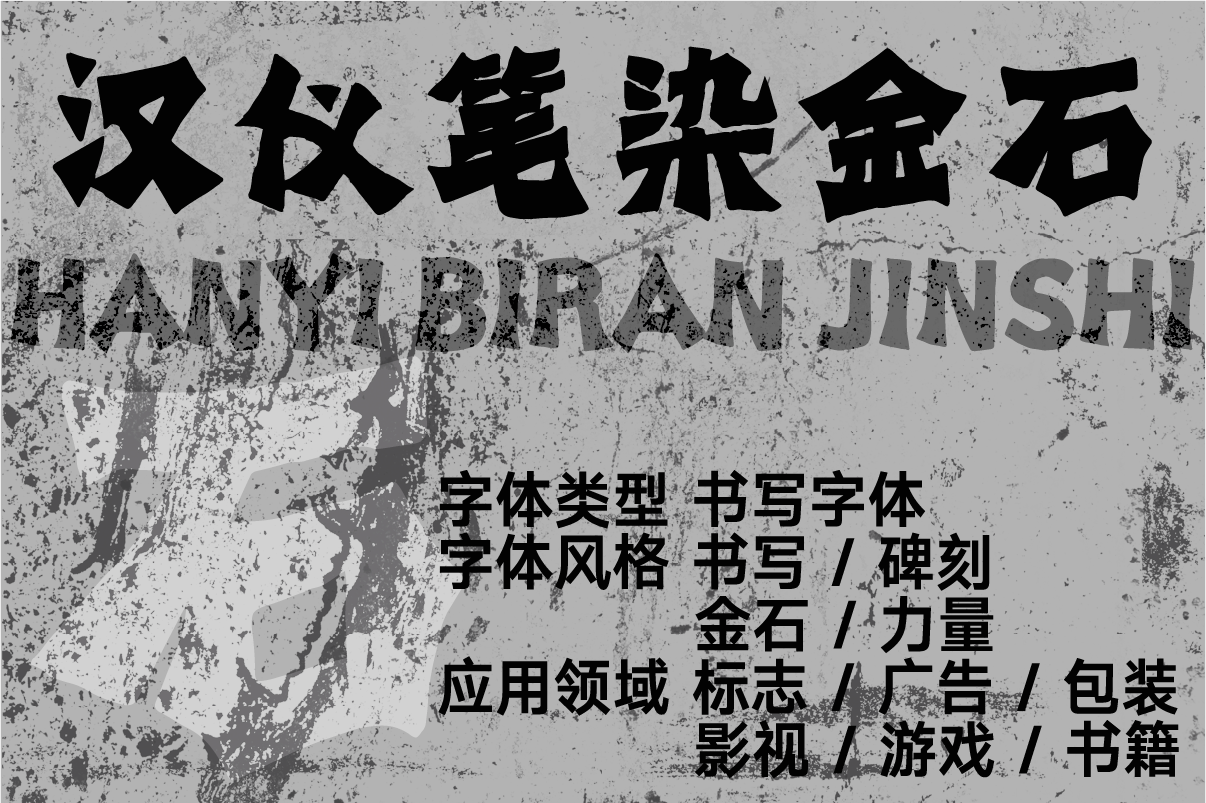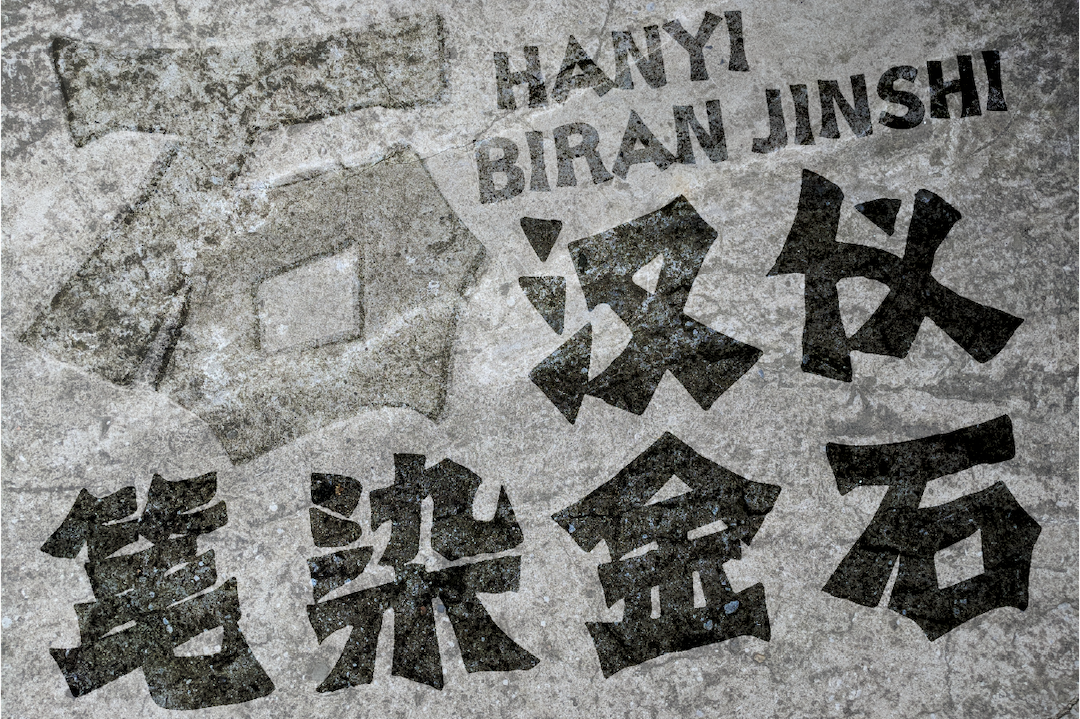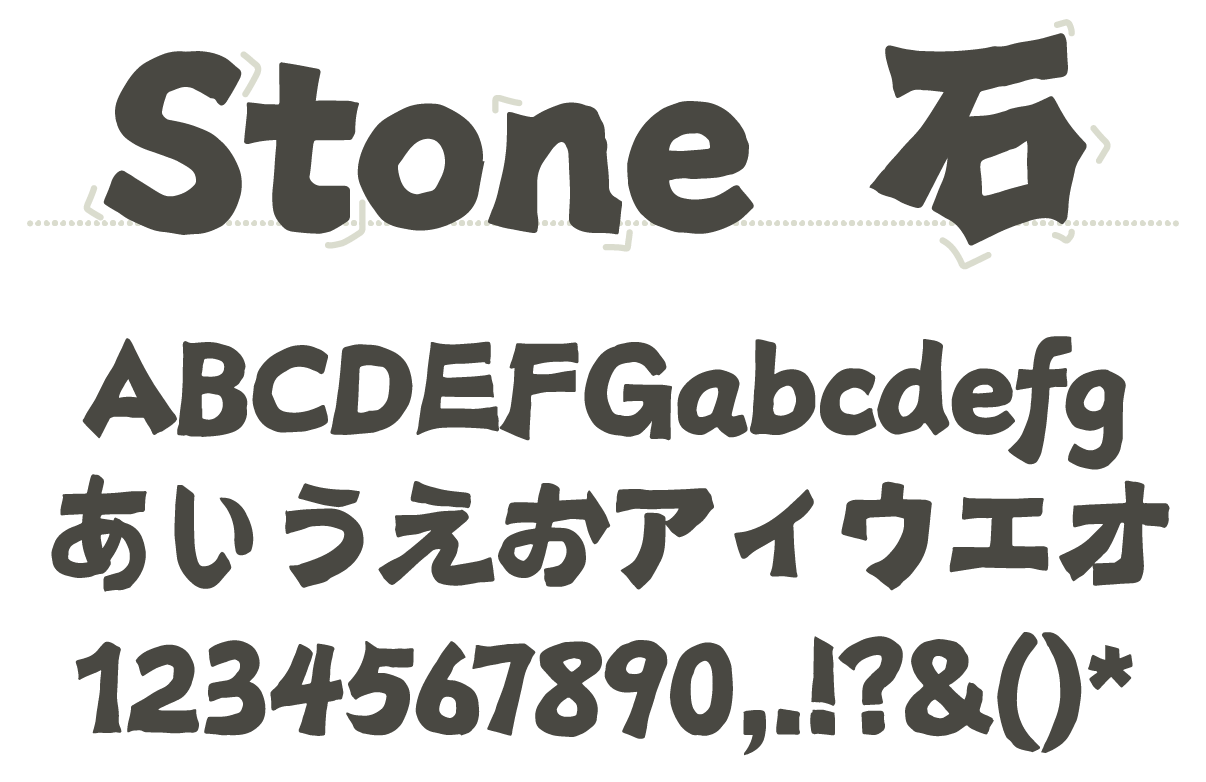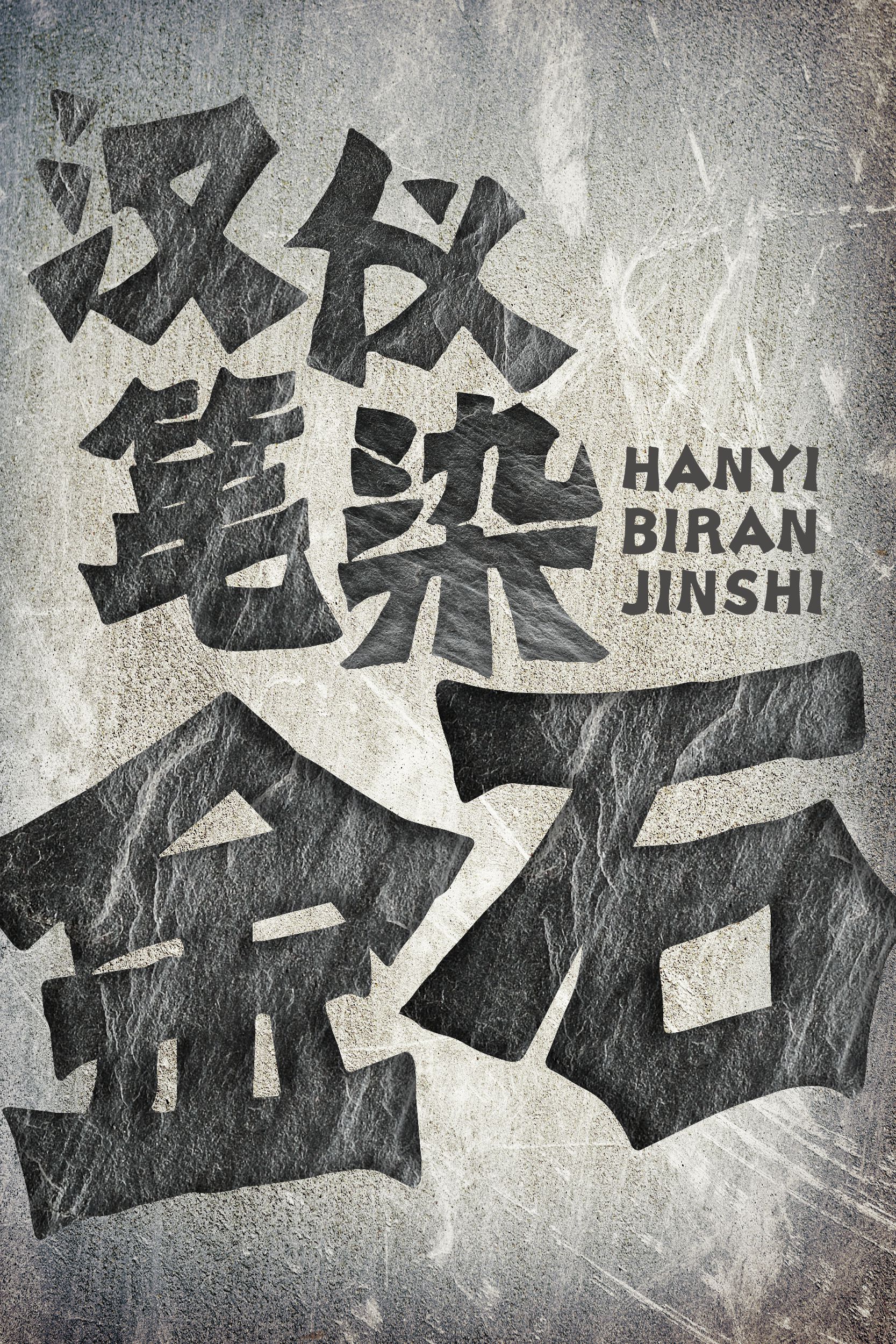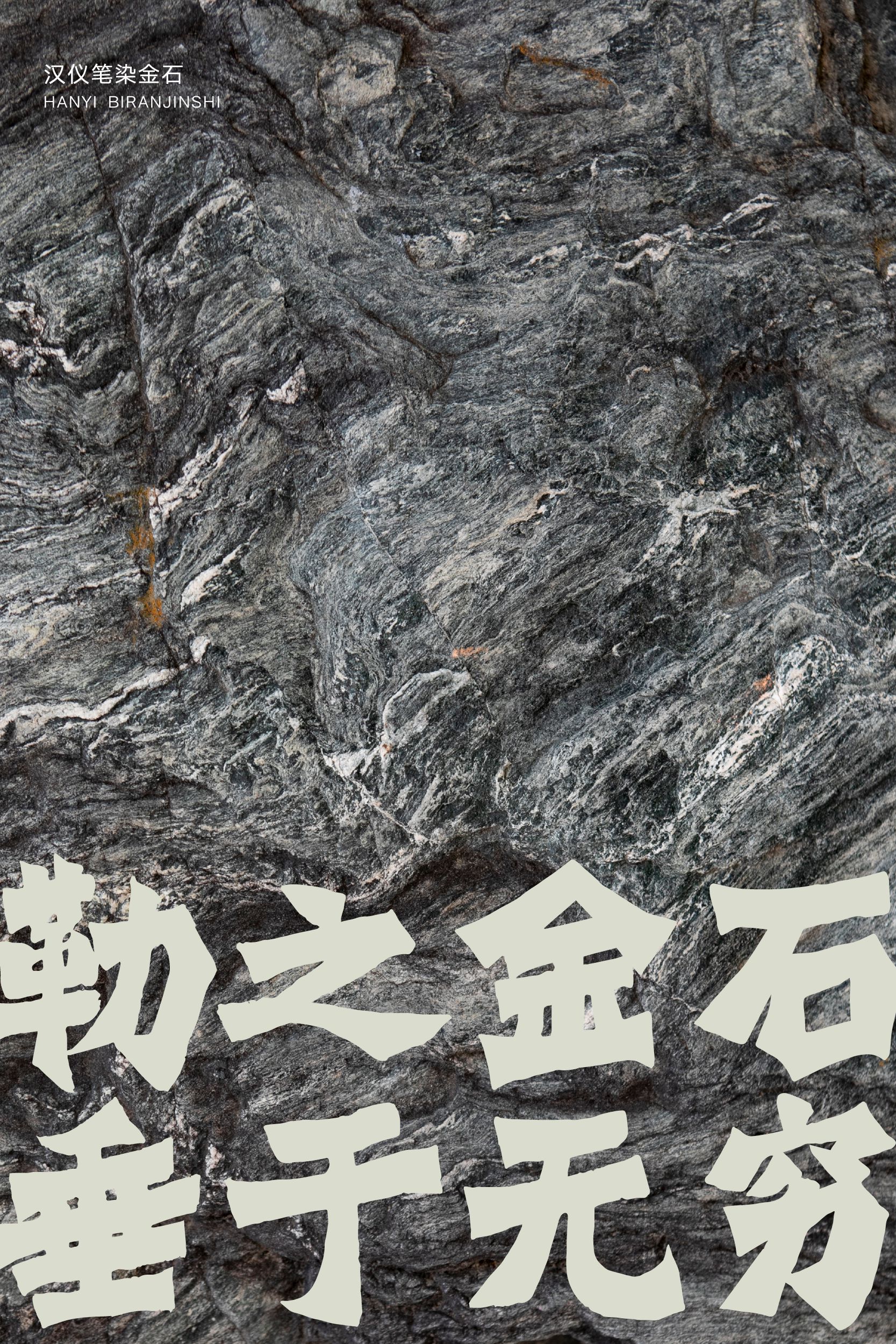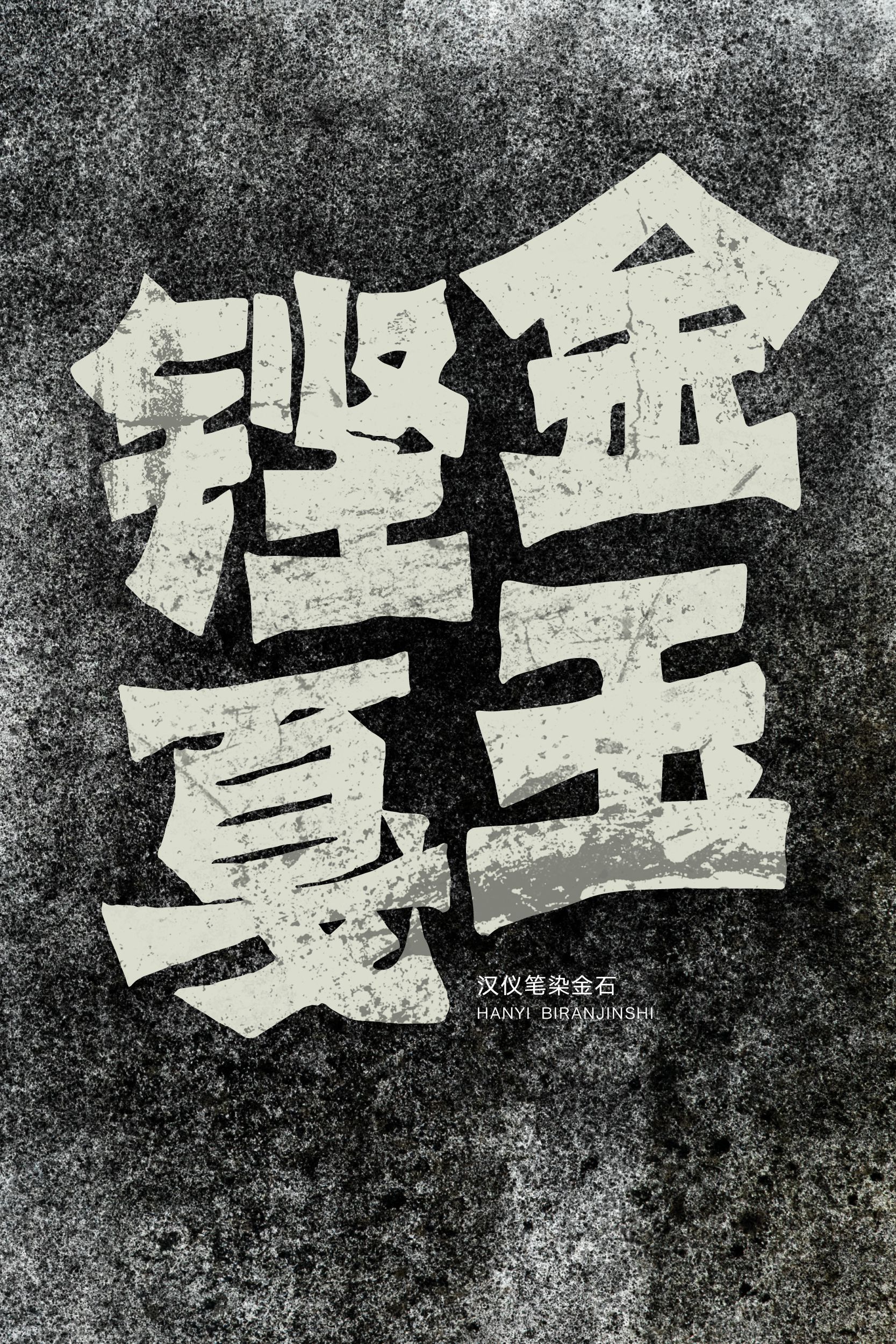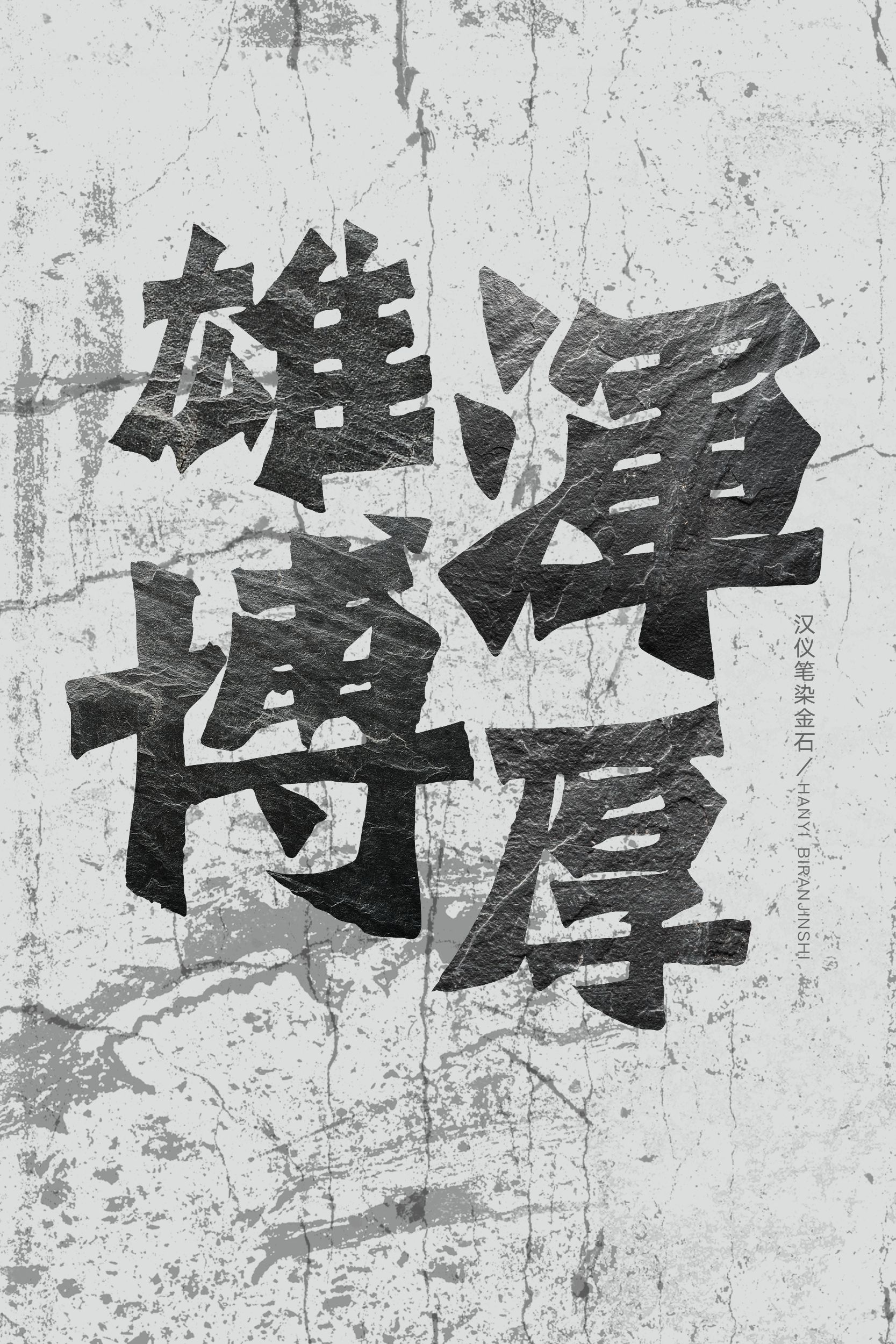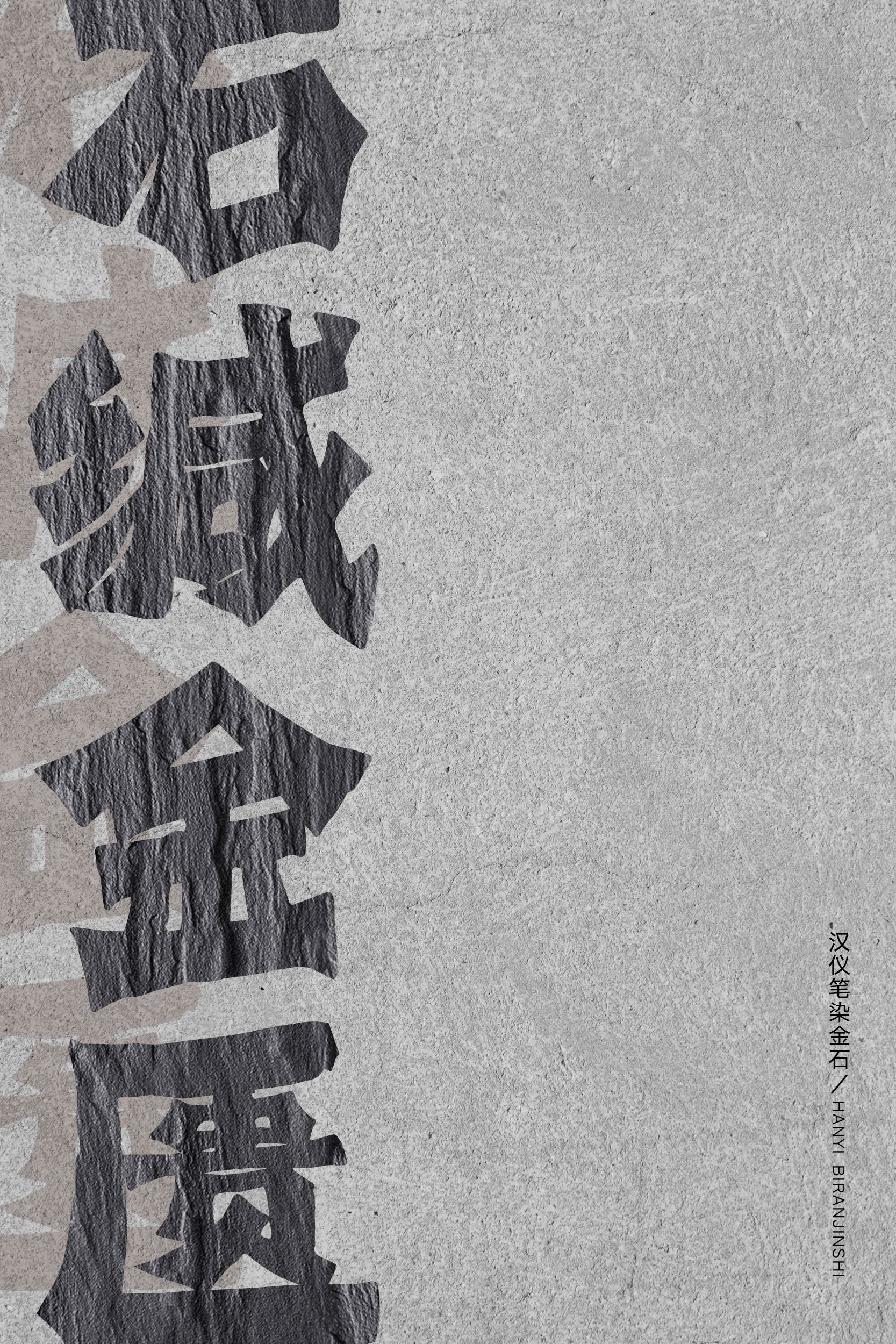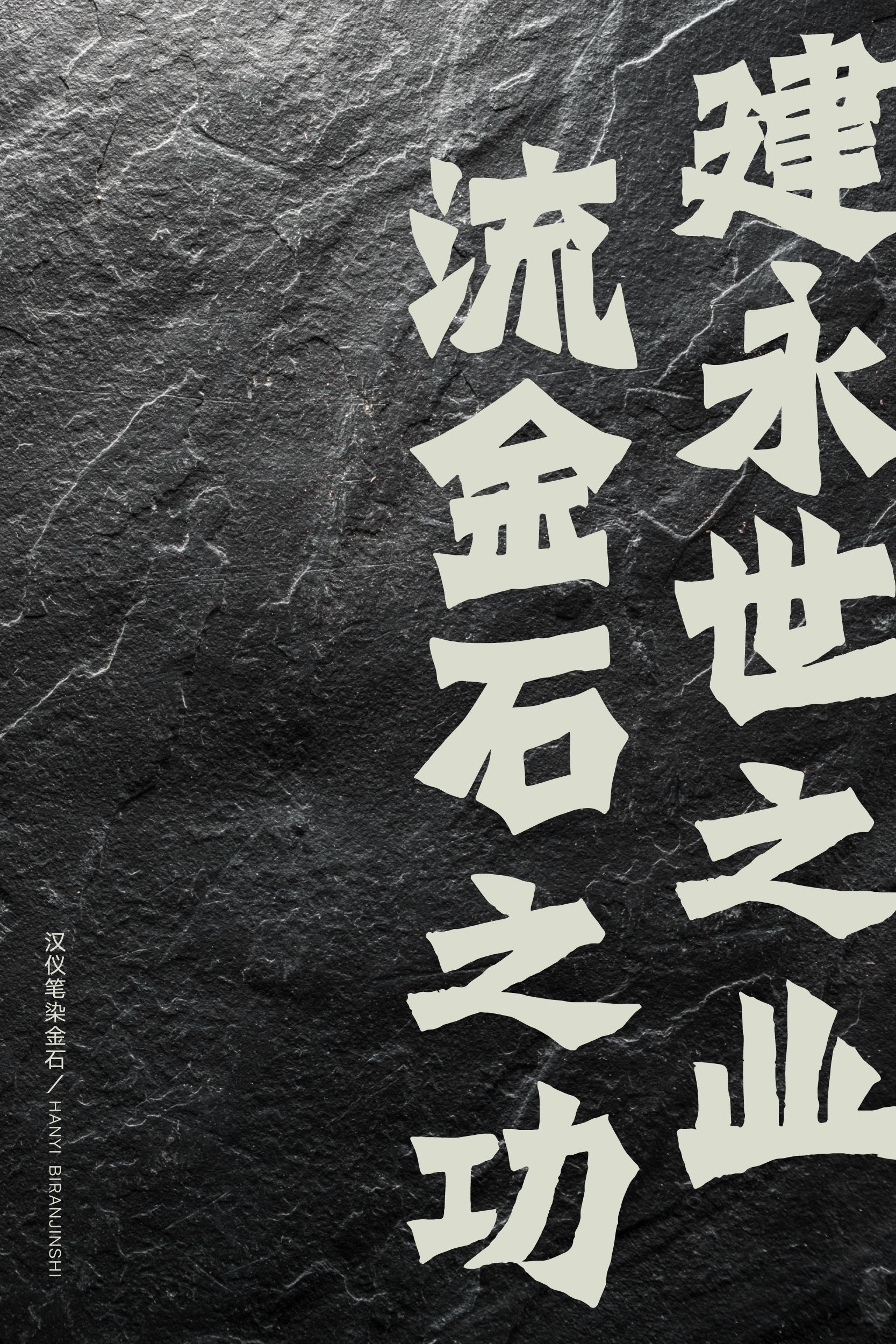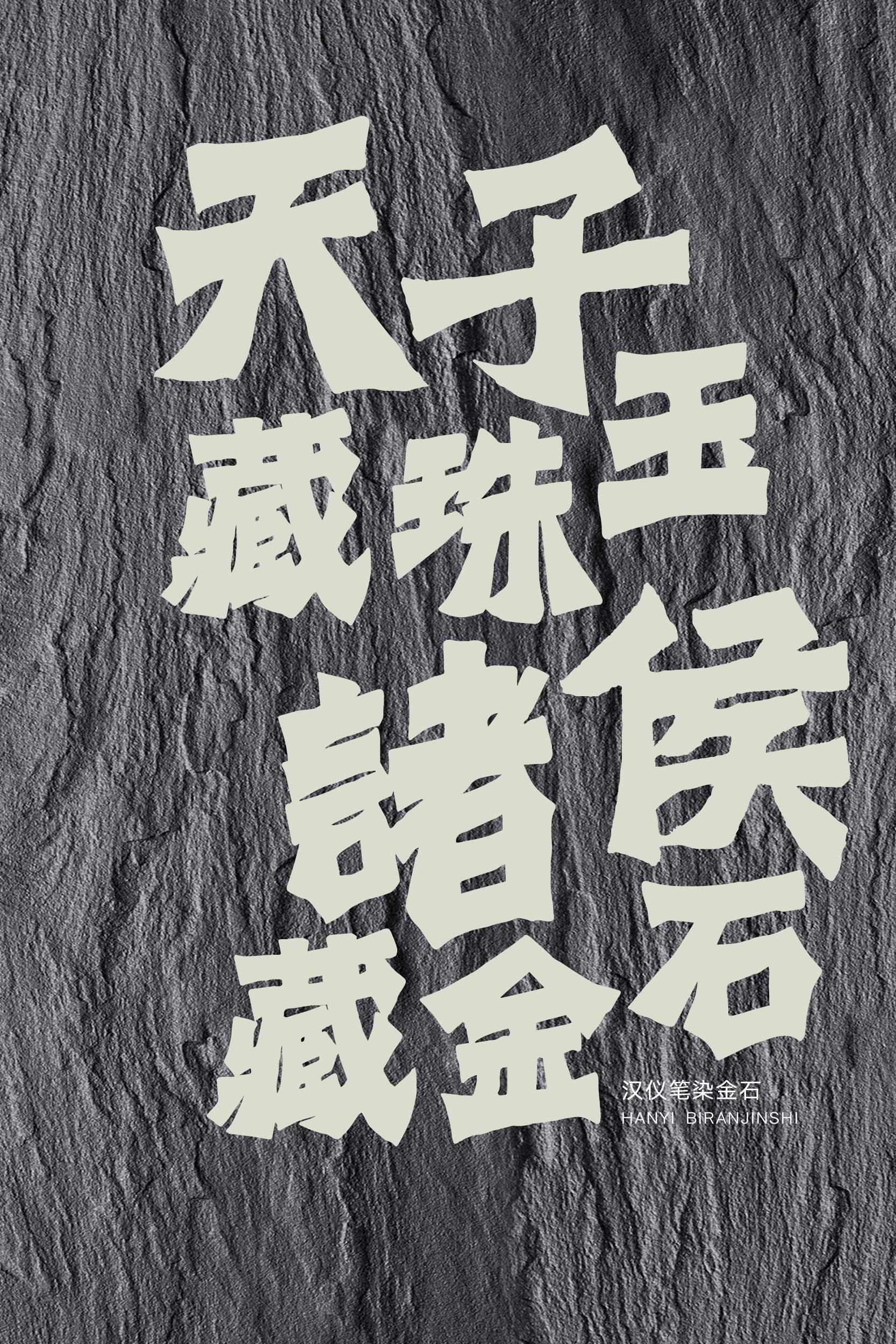
汉仪笔染金石
汉仪笔染金石,坚硬厚重若金石,方折浑厚,是一款具有碑刻味道的书写字体。字形倾斜,笔画顿挫有力,斑驳的边缘保留金石碑刻古朴的韵味。这款力量感十足又充满丰富细节的字体适合作为标题字体应用于特色餐饮、民俗节日、传统文化等多样的使用场景。
整体如金石坚硬厚重。
字形有倾斜变化,重心上提而结构稳定。
笔画方直有力,抑扬顿挫。
边缘斑驳,保留金石拓片质感。
西文部分保留金石一般厚重的形态,中西文方硬朴厚的风格和谐统一。